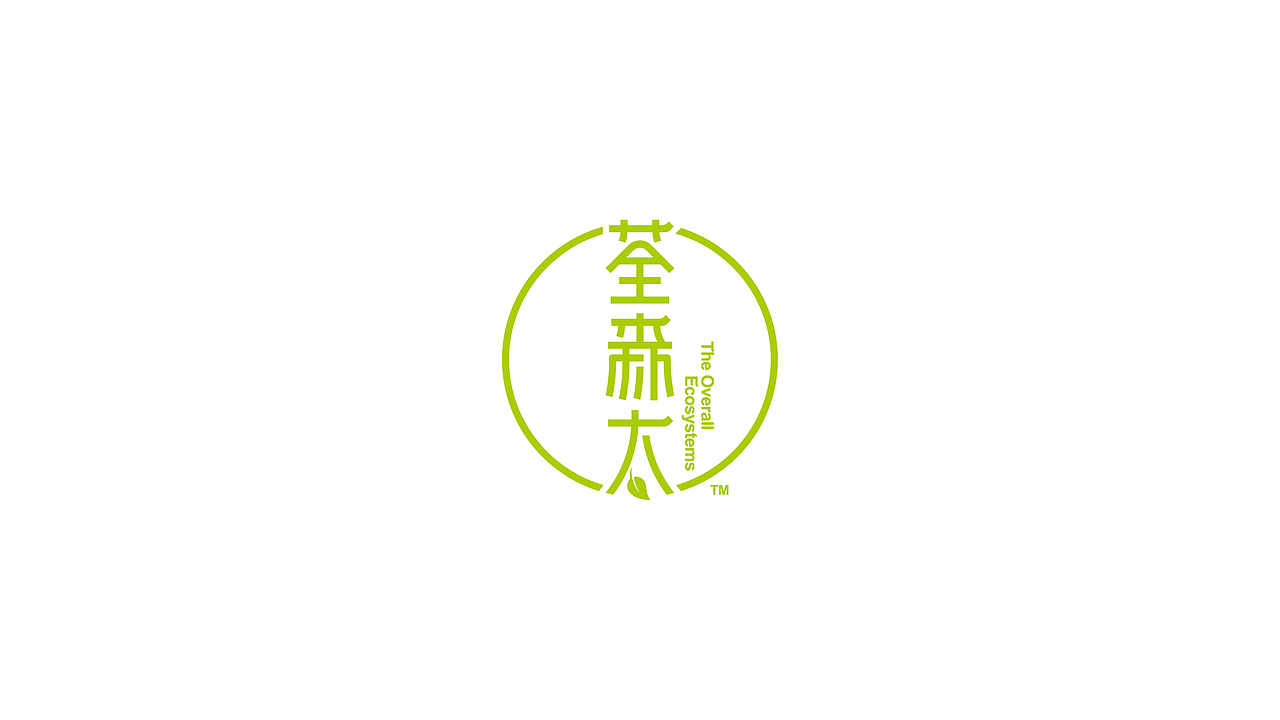
荃森太-品牌包裝設計
荃森太是邢者™团队中邓力骢的自主产品,邓在成都创业做现代农业,锁定宁乡猪的新型养殖。2016年是他最忙的一年,穿梭于湖南-成都-广州-银川,只为做好一份处女座的腊肉!
logo的设计采用简单明了的字体设计展示,运用在包装上美观大方又不失识别性。
荃森太的包装设计理念主要是传统,为了在保证美观的前提下节省成本,我们做了很多尝试。
真的是设计师最佳节省成本的案例了(此处应该有掌声!)<br>无论在品牌设计方面还是装饰设计方面,设计师都不仅仅是帮您美化需求,更重要的是在合理的范围内帮您节省成本和规避不必要的花费!<br>礼盒从包装纸张到印刷纸张都是我们亲自挑选去做实验,最终从成本和效果上考虑选用350g的进口牛卡做包装纸材,设计折盒,并自己制图做小样。
荃森太的包装设计理念主要是传统,为了在保证美观的前提下节省成本,我们做了很多尝试。
真的是设计师最佳节省成本的案例了(此处应该有掌声!)
无论在品牌设计方面还是装饰设计方面,设计师都不仅仅是帮您美化需求,更重要的是在合理的范围内帮您节省成本和规避不必要的花费!
礼盒从包装纸张到印刷纸张都是我们亲自挑选去做实验,最终从成本和效果上考虑选用350g的进口牛卡做包装纸材,设计折盒,并自己制图做小样。
在工作室展开手工大作战
手工好不好,就看下刀子的方式了
在工作室展开手工大作战
手工好不好,就看下刀子的方式了
其中对于节省成本上最大的一个创新就是省去了手提袋,在包装上我们增加了一个纸带,在这个纸带袋上我们花费的经历是最多的。
为了增加手作感,增加拎手部分的手感,美观性,我们做了很多尝试。最后锁定2mm直径的细麻绳。<br>第一个成品手工打造的礼盒小样长这样
其中对于节省成本上最大的一个创新就是省去了手提袋,在包装上我们增加了一个纸带,在这个纸带袋上我们花费的经历是最多的。
为了增加手作感,增加拎手部分的手感,美观性,我们做了很多尝试。最后锁定2mm直径的细麻绳。
第一个成品手工打造的礼盒小样长这样
缠绕麻绳和条带的设计是整个标志最增色的地方,都是纯手工的缠绕。当时我不止一次询问邓,这个在人工上的花费可远远高出了材料本身。邓跟我确认,他的人工要比想象的多的多,有的是人和时间去做这种事情。
结果就是他们按时按量的完成了第一批的既定生产任务。
缠绕麻绳和条带的设计是整个标志最增色的地方,都是纯手工的缠绕。当时我不止一次询问邓,这个在人工上的花费可远远高出了材料本身。邓跟我确认,他的人工要比想象的多的多,有的是人和时间去做这种事情。
结果就是他们按时按量的完成了第一批的既定生产任务。
还做了一个快递测试,结果在场的小伙伴都直接笑喷
红纸勾起了小时候的回忆,剪喜字,随手来一个
包装效果图
封口处用火漆封腊
当时最后的时间比较紧张,邓下午2点的灰机要去成都谈年前的合作,而我们紧张的做最后的产品拍摄。当天的成片
内部是两筒腊肠,四块腊肉,真空包装后包牛皮纸扎麻绳。
邓亲手操刀设计的小四折页,放在包装中,介绍吃法和工艺
那天下着小雨,邓坐上朋友的车赶往机场
最后来看看荃森太的动态logo